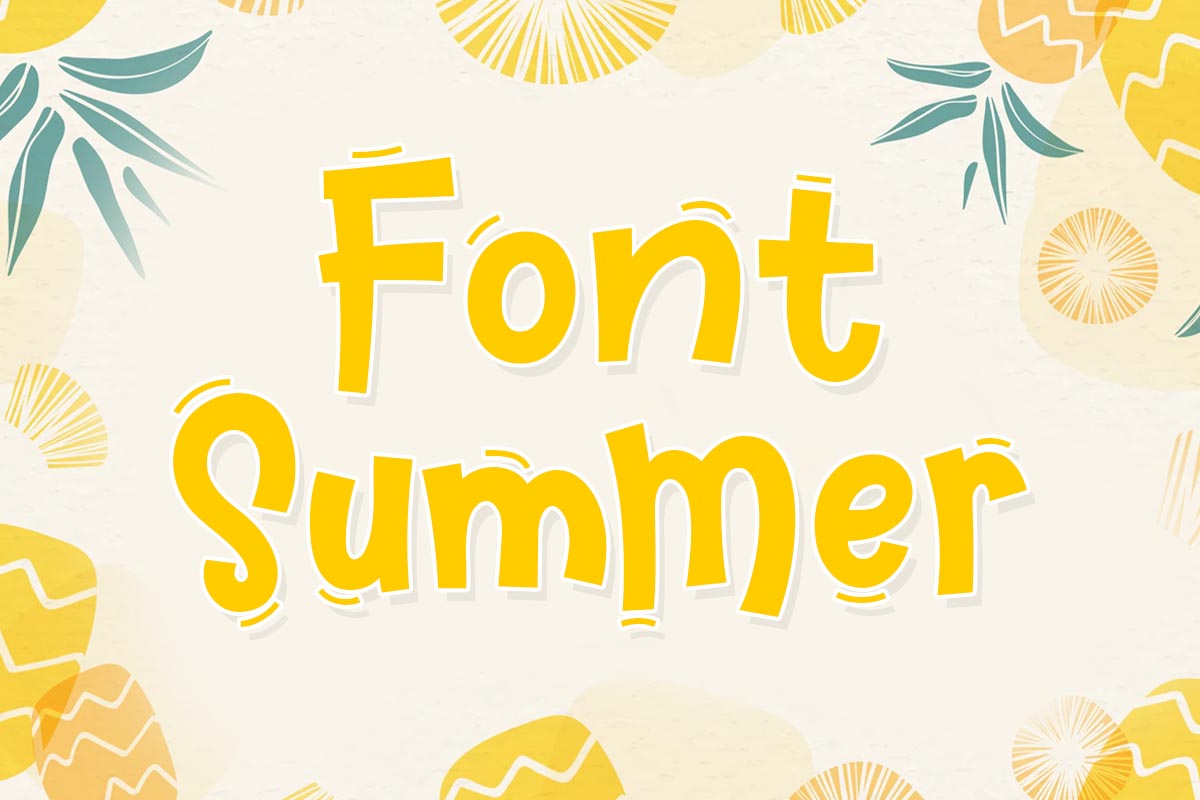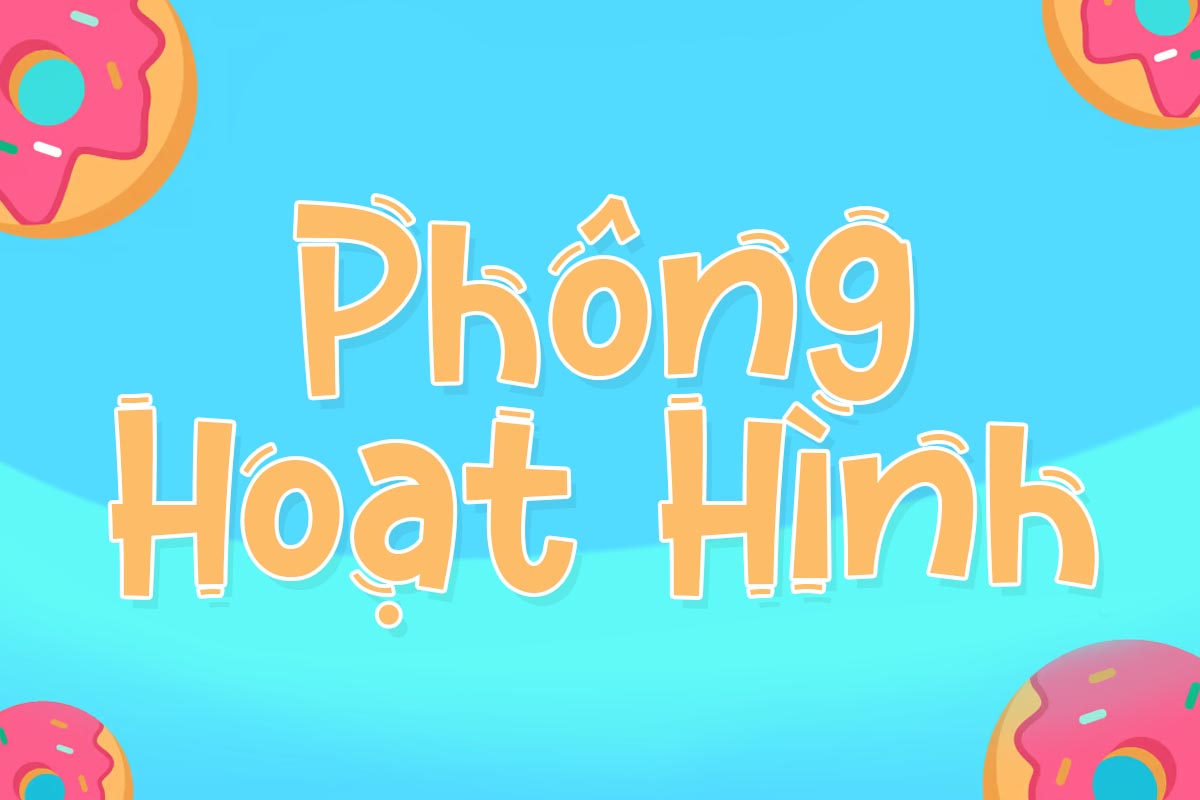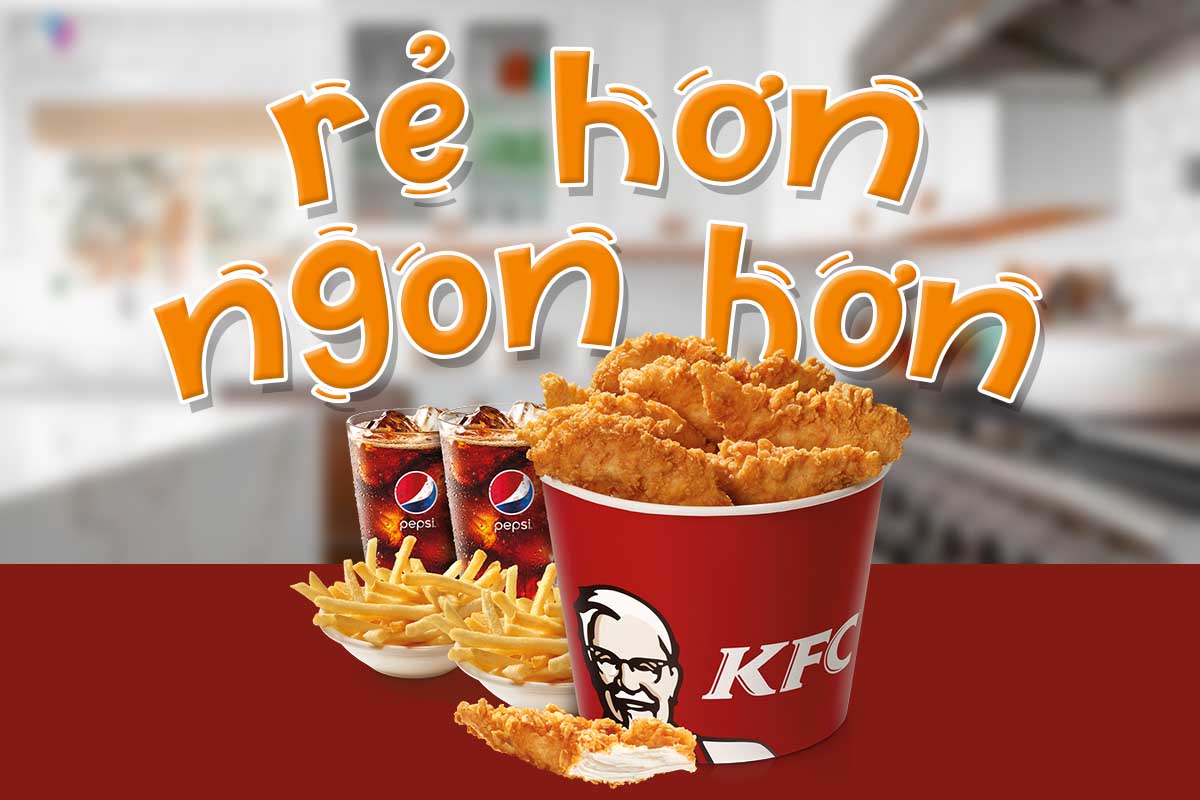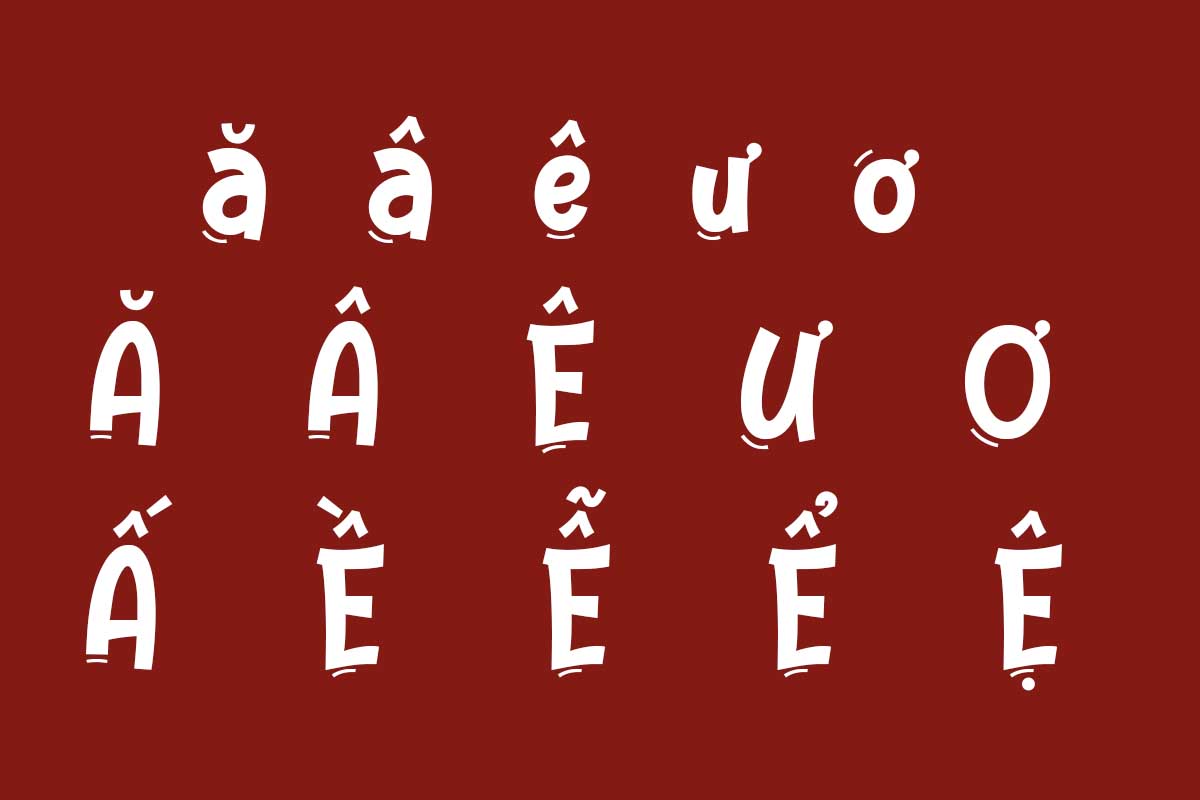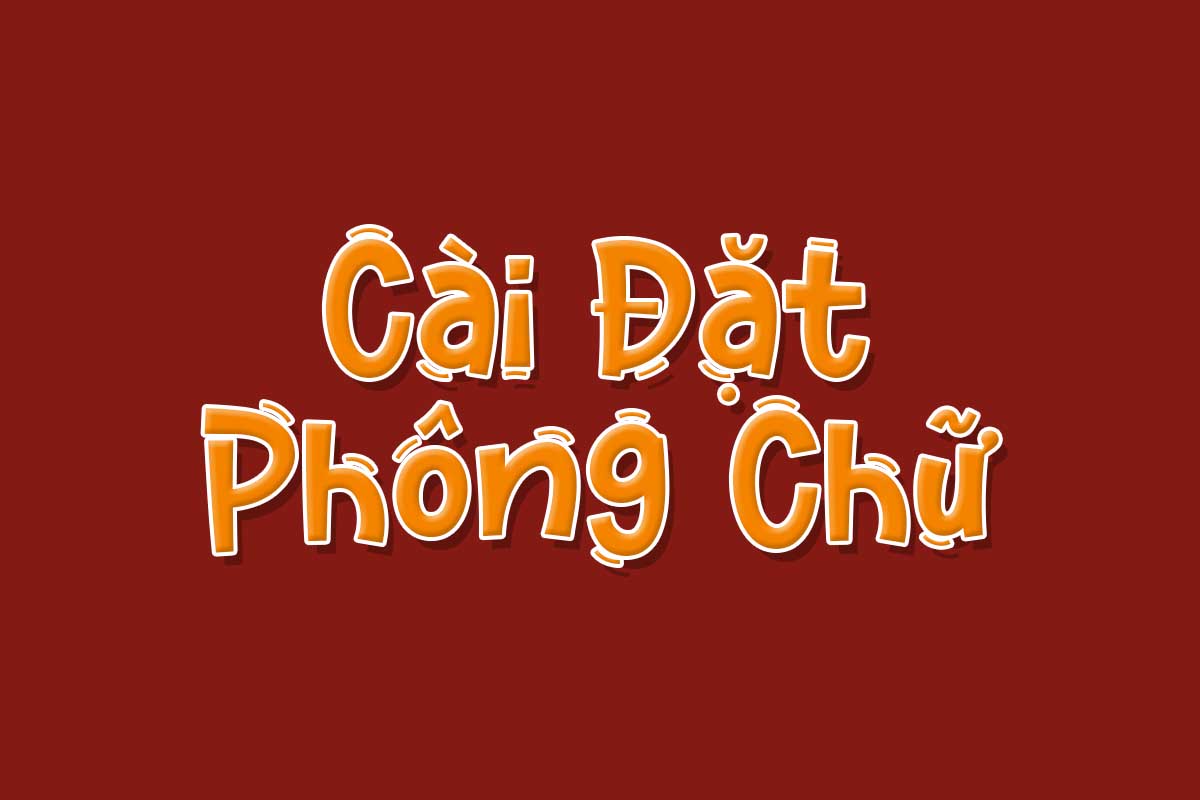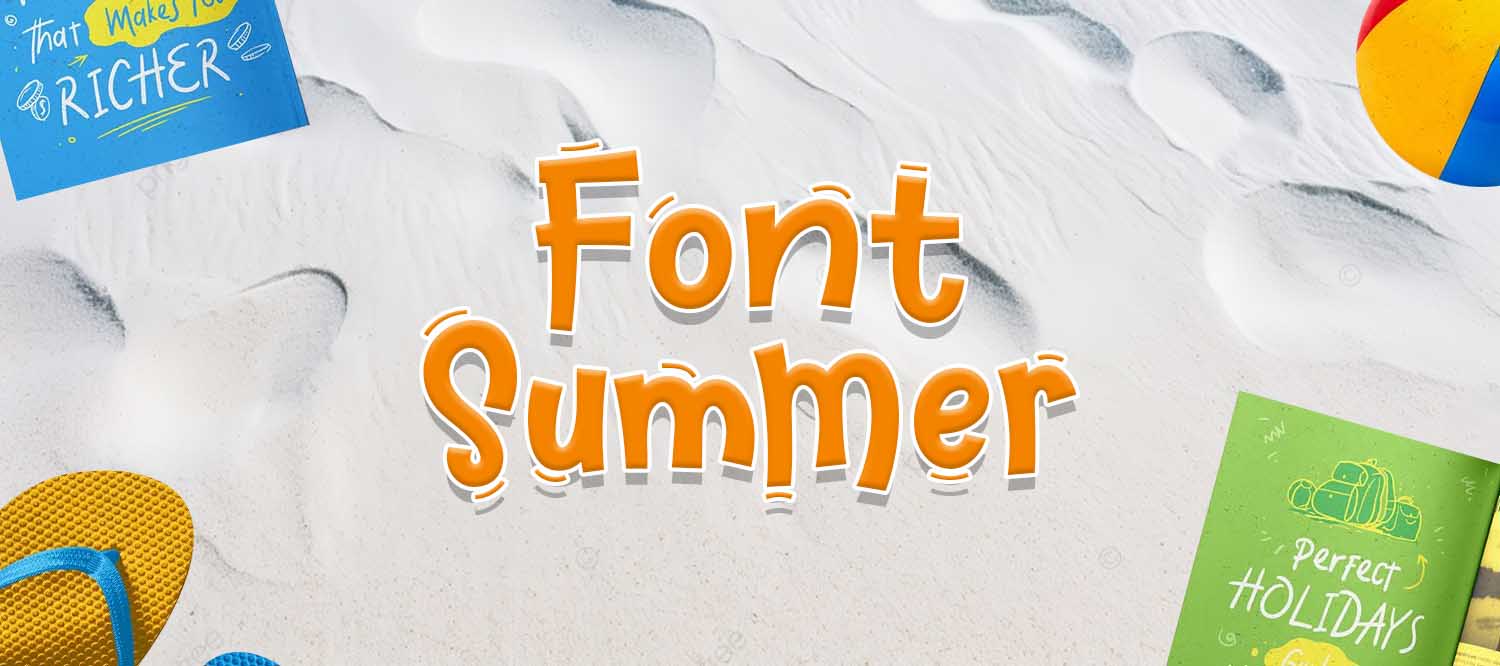
![[Miễn Phí] Font Hoạt Hình Summer Việt Hóa Tươi Sáng, Dễ Thương](https://cdn.s99.vn/cloud/font-chu-viet-hoa-MTD-Summer-Show-anh-6.jpg)
Mỗi mùa hè về, nhà thiết kế, marketer hay các bạn yêu thích sáng tạo đều mong muốn tìm kiếm một phong cách chữ mới mẻ, mang hơi thở rực rỡ và đầy sức sống. Trong vô vàn lựa chọn font hiện nay, font hoạt hình Summer là một cái tên nổi bật với nét chữ vui nhộn, màu sắc tươi sáng và khả năng truyền tải cảm xúc mùa hè một cách gần gũi, sinh động.
Không chỉ phù hợp với nhiều dự án thiết kế cá nhân hay thương mại, font Summer còn được Việt hóa đầy đủ, sẵn sàng hỗ trợ người dùng trong mọi ngữ cảnh tiếng Việt. Bài viết dưới đây sẽ giúp bạn khám phá chi tiết về bộ font chữ đang rất được yêu thích này – từ phong cách, ứng dụng, cách tải về cho đến hướng dẫn sử dụng thực tế.
Font Summer là kiểu chữ được thiết kế theo phong cách hoạt hình nghĩa là mỗi nét chữ đều mang đến cảm giác ngộ nghĩnh, vui nhộn và giàu tính biểu cảm. Font sở hữu các đường nét bo tròn mềm mại, không quá cứng nhắc như font sans-serif truyền thống, nhưng cũng không cầu kỳ như các bộ script viết tay.
Điều đặc biệt nằm ở sự bất đối xứng nhẹ nhàng trong từng chữ cái, khiến chúng giống như được vẽ tay ngẫu nhiên – tạo nên cảm giác trẻ thơ, tự nhiên, gần gũi. Sắc cam vàng được sử dụng trong ảnh càng làm nổi bật tinh thần mùa hè – gợi nhớ đến ánh nắng, ly nước cam mát lạnh hay tiếng cười giòn tan trong những buổi cắm trại cuối tuần.
Font Summer là một đại diện tiêu biểu cho tinh thần "hoạt hình" – luôn tươi vui, lạc quan và dễ dàng khiến người xem mỉm cười ngay từ cái nhìn đầu tiên.
Để được xếp vào nhóm font hoạt hình, một bộ font cần sở hữu những đặc trưng rất riêng – và font Summer đáp ứng gần như trọn vẹn các tiêu chí đó.
Trước tiên là tạo hình chữ mang tính "thị giác chuyển động", nghĩa là nhìn vào bạn có thể cảm nhận các ký tự đang nhún nhảy, lắc lư một cách sống động. Thứ hai là tính cá nhân hóa cao – các chữ cái có độ biến thiên nhất định về chiều cao, độ nghiêng và khoảng cách – giúp font không bị nhàm chán khi sử dụng trong thiết kế.
Và cuối cùng là hiệu ứng đổ bóng được xử lý nhẹ nhàng, tạo chiều sâu mà không làm rối mắt. Tất cả những yếu tố này khiến người dùng dễ dàng liên tưởng đến các tiêu đề trong phim hoạt hình, truyện tranh hay các trò chơi thiếu nhi – nơi font chữ đóng vai trò tạo cảm xúc chủ đạo.
Với phong cách đáng yêu và dễ kết hợp, font hoạt hình Summer có thể ứng dụng rộng rãi trong nhiều dạng thiết kế.
Trước hết là các sản phẩm in ấn mùa hè như poster quảng cáo, biển treo sự kiện, tờ rơi chương trình hè... Những dự án này thường yêu cầu font chữ dễ đọc, có tính năng động cao và gợi cảm giác tươi mới điều mà font Summer làm rất tốt.
Ngoài ra, với xu hướng làm video ngắn đang phát triển mạnh, font Summer còn xuất hiện nhiều trong CapCut, TikTok, Reels đặc biệt trong các video hài hước, hướng dẫn hoặc giới thiệu sản phẩm cho trẻ em.
Không dừng lại ở đó, font còn phù hợp để làm bìa thiệp sinh nhật, sách học sinh, menu quán kem hay áo thun cho team đi biển. Tóm lại, font hoạt hình Summer là lựa chọn an toàn nhưng cũng đầy sáng tạo cho bất kỳ ai đang làm việc với nội dung hướng đến sự trẻ trung và cảm xúc tích cực.
Một trong những vấn đề thường gặp khi lựa chọn font hoạt hình là khả năng hỗ trợ tiếng Việt không đầy đủ – điều này dễ dẫn đến lỗi hiển thị dấu, chữ bị méo, mất nét hoặc mất cân đối trong thiết kế. Tuy nhiên, font Summer đã khắc phục hoàn toàn nhược điểm này nhờ được Việt hóa chỉn chu bởi team MTD – một nhóm chuyên thực hiện Việt hóa font chất lượng cao, uy tín trong cộng đồng thiết kế.
Toàn bộ các dấu tiếng Việt như: ă, â, ê, ô, ơ, ư, đ… đều được tinh chỉnh tỉ mỉ để đồng bộ hoàn toàn với form chữ gốc. Điều này không chỉ đảm bảo tính thẩm mỹ mà còn giữ nguyên cảm xúc hoạt hình dễ thương của font khi sử dụng cho tiếng Việt.
Với bản Việt hoá đầy đủ từ MTD, bạn có thể yên tâm dùng font Summer trên mọi nền tảng: từ phần mềm đồ họa chuyên nghiệp như Adobe Illustrator, Photoshop cho đến các công cụ sáng tạo phổ biến như Canva, CapCut, PowerPoint…
Font hiển thị mượt mà, rõ ràng, sắc nét và cân đối, phù hợp để dùng cho in ấn, thiết kế số, trình chiếu hoặc tạo banner cỡ lớn mà không lo gặp lỗi font hay vỡ chữ.